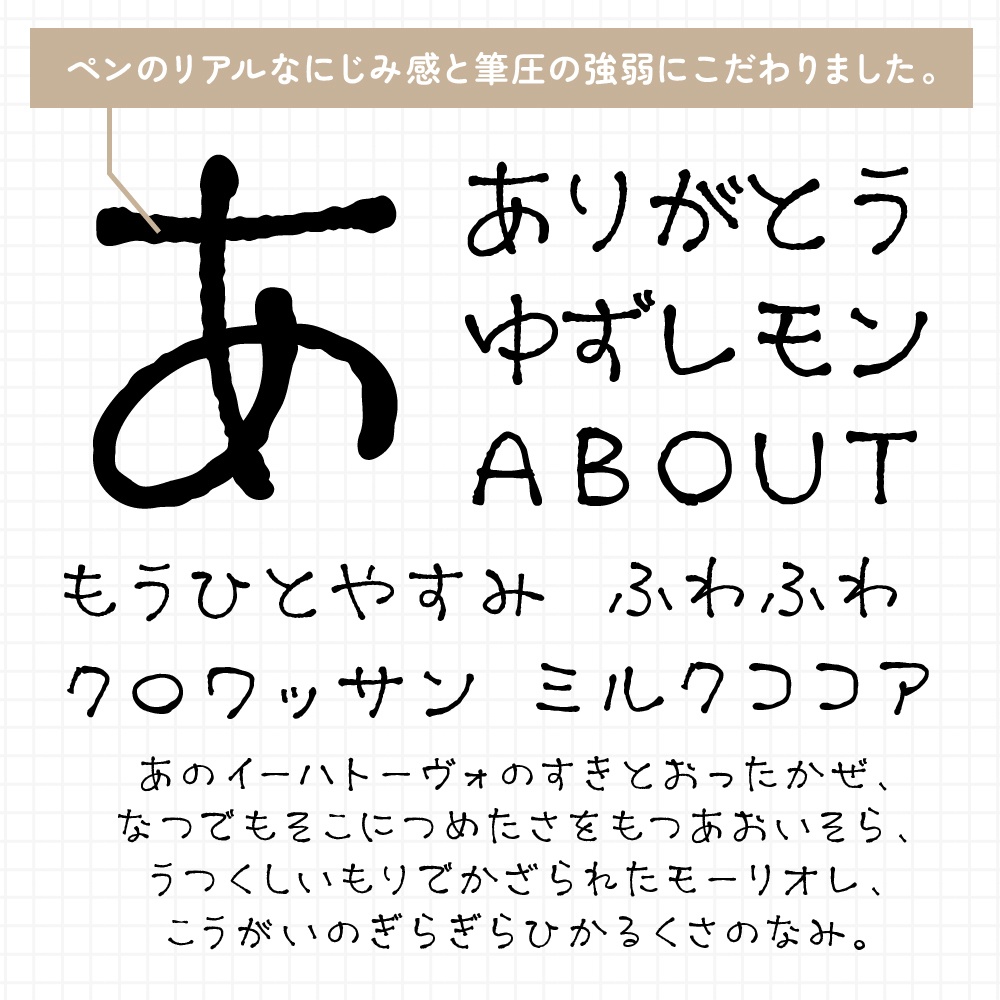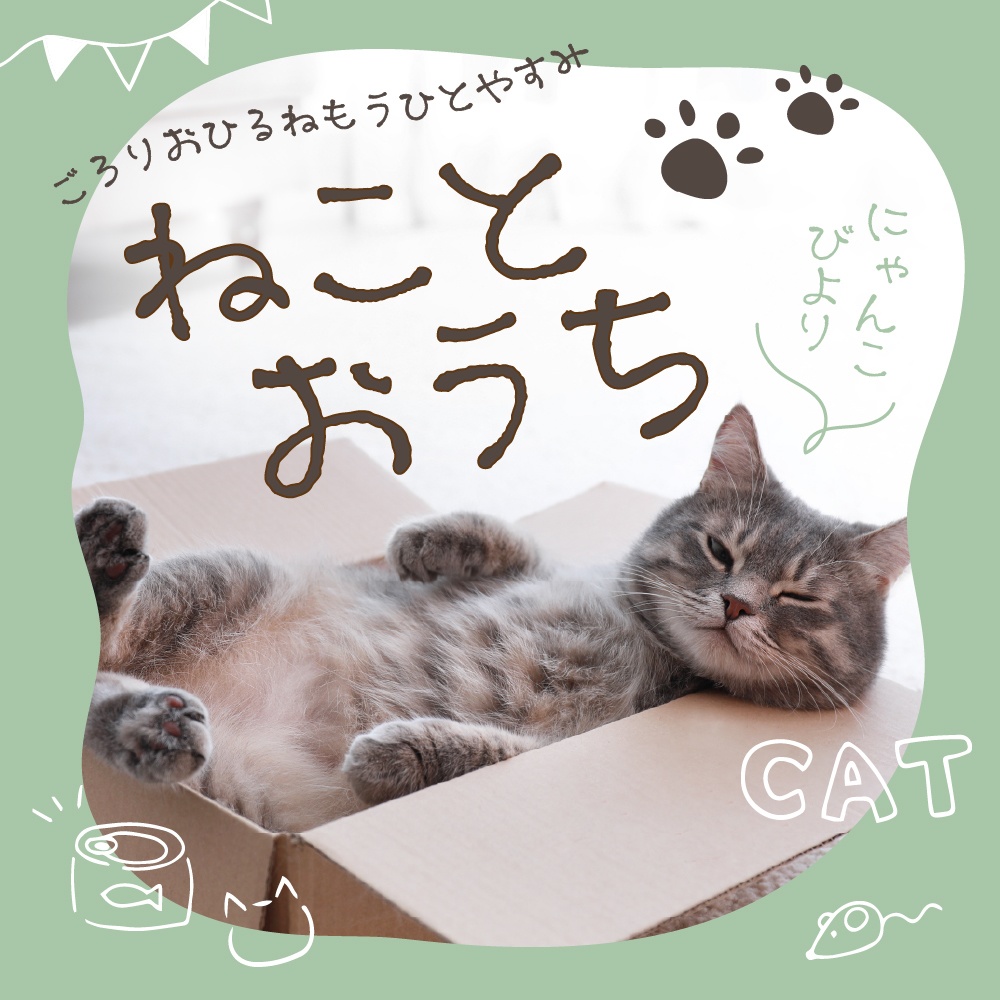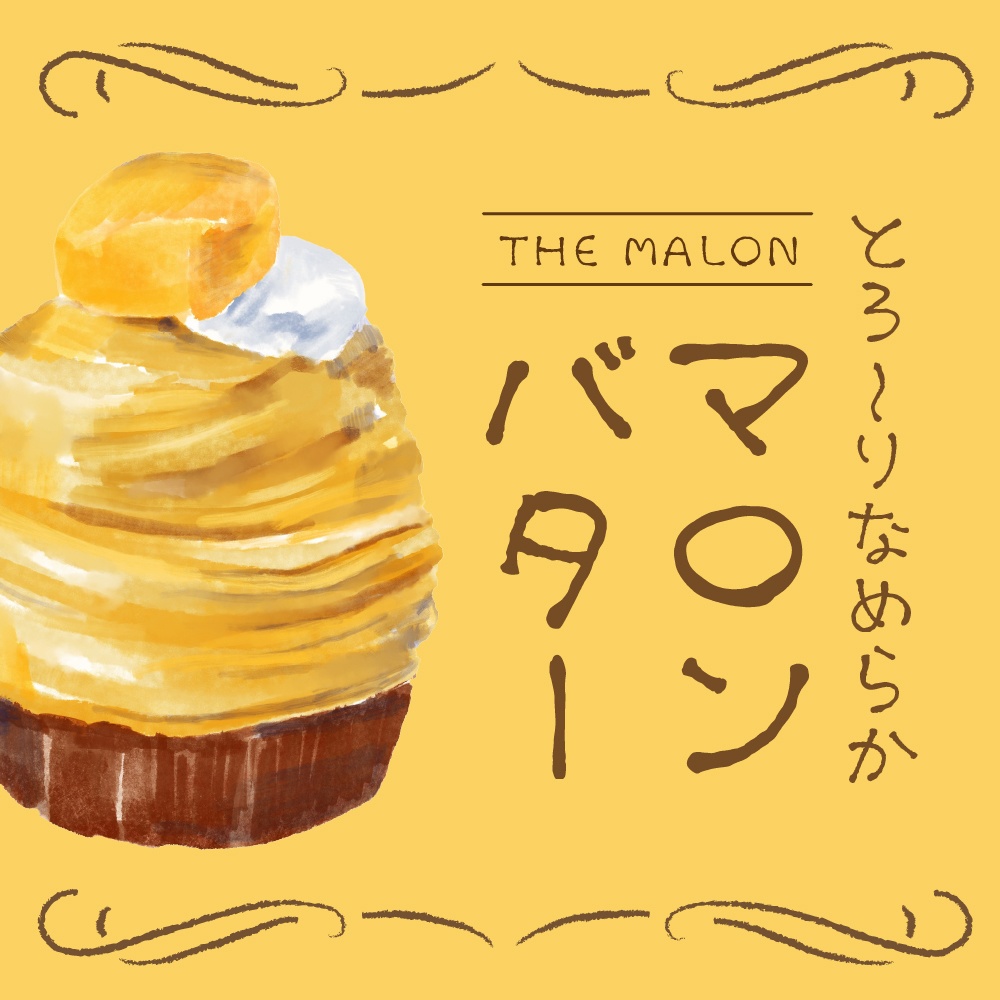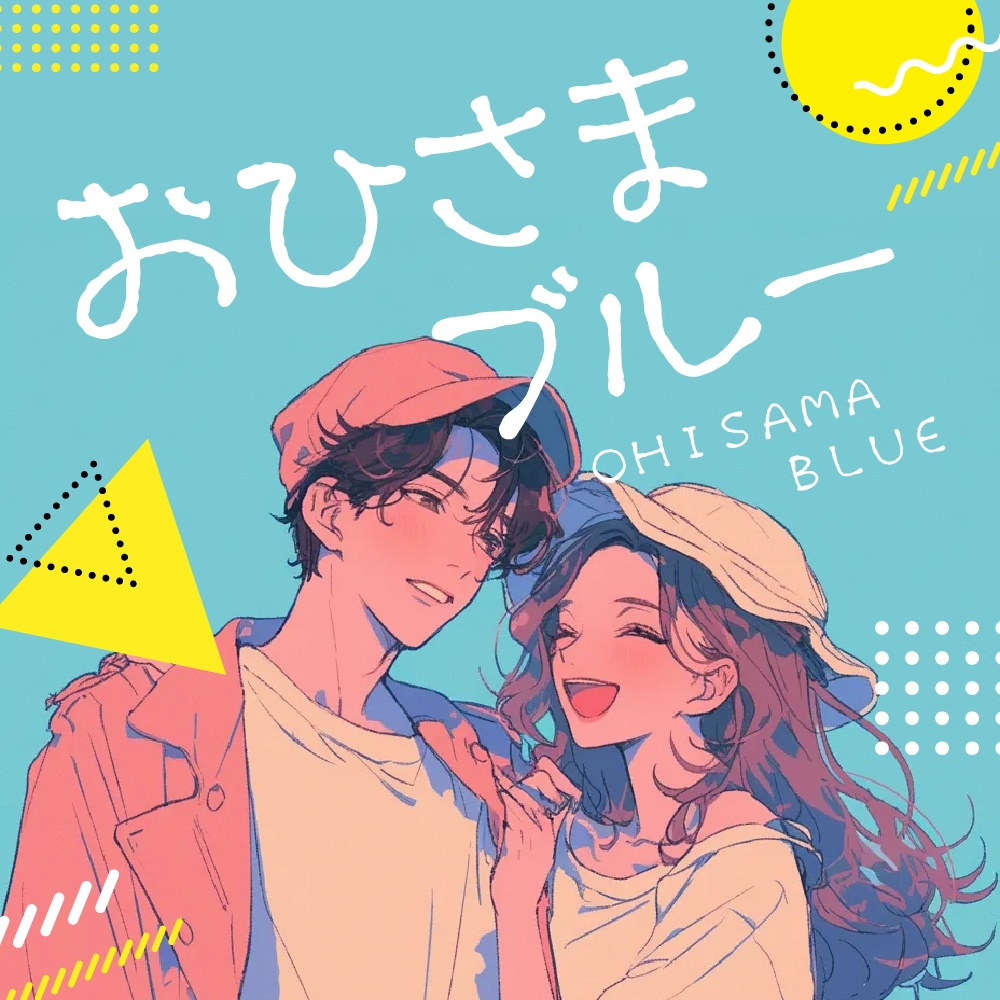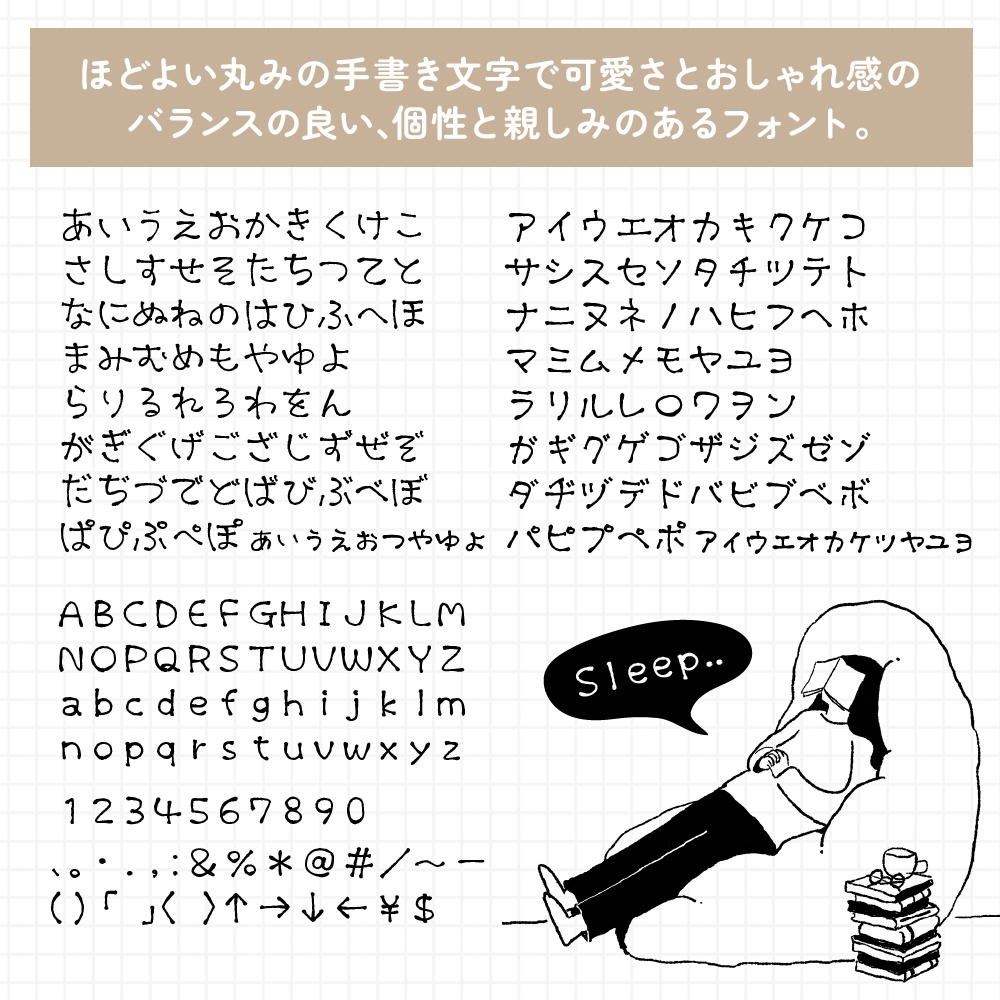
【無料verあり】手書きフォント ちるあうと
ほどよい丸みの手書き文字で、 可愛い親しみと個性あふれる 手書きフォント「ちるあうと」です。 レトロ感やエモさもあるおしゃれな雰囲気に。 ペンで描いたインクのにじみや筆圧の強弱を残し、 表情のあるタイトルや文章に仕上がります。 商用・個人を問わず利用可能です。 WEBサイトやデザインバナー作成、同人作品や印刷物等 お好きな用途でご使用いただけます。 クレジット等の表記は特に必要ありません。 ○収録文字 フルVer:ひらがな、カタカナ、数字、アルファベット、一部約物 無料ver:カタカナのみ ○フォント形式:OpenTypeフォント ■免責事項 著作権は放棄しておりません。 無断で商標登録・共有・販売・再配布することは禁止です。 フォントを使用して発生した、いかなるトラブル・損害について一切責任を負いません。 本商品はデジタルデータのため、購入後のダウンロードや インストール方法、ご利用環境(OS・PC設定等)に関するトラブルについては対応できかねますので、ご購入前に対応OSやフォントのインストール方法をご確認のうえ、ご了承いただいた上でのご購入をお願いいたします。 購入状況やダウンロードに関するご不明点につきましては、BOOTH事務局へお問い合わせください。 手書きフォント,日本語フォント,おしゃれ,かわいい,レトロ,ペン字,マーカー,フリーフォント,無料,無料フォント,フリー